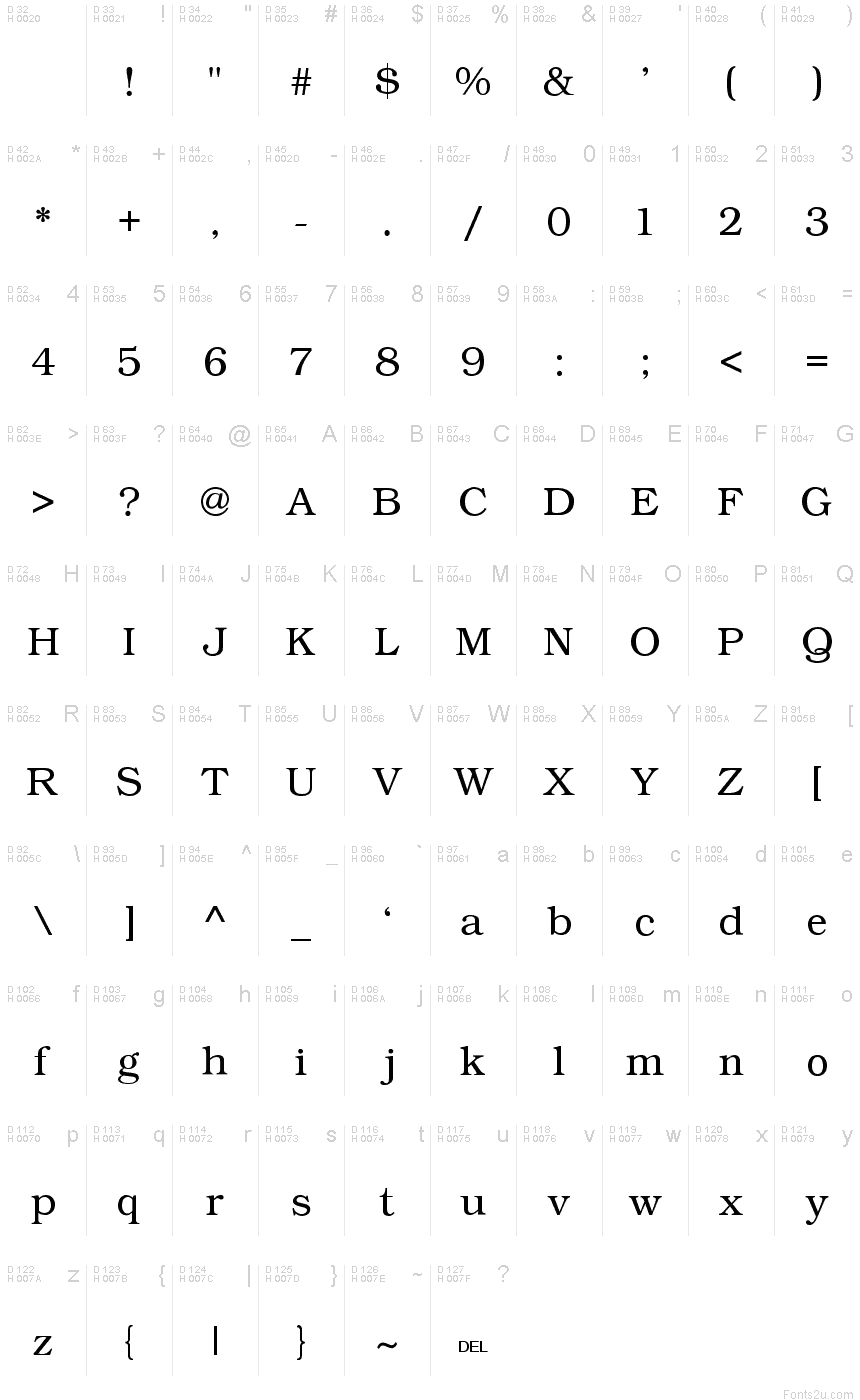
Kacst Book від URW Design and Development — це безкоштовний антиквовий шрифт зі спокійним, каліграфічним характером. Широкі вигини, чіткі штрихи та м’яко змодельовані малі літери створюють атмосферу традиційного читального залу, не виглядаючи при цьому занадто суворо.
Цей безкоштовний шрифт природно пасує для редакційних заголовків, літературних обкладинок, культурних плакатів, музейних програм та стриманих титульних карток. Його щедрі форми мають достатню виразність для коротких заголовків і перших сторінок, тоді як контраст між плавними вигинами та впевненими зарубками надає кожній роботі збалансованого, академічного тону.